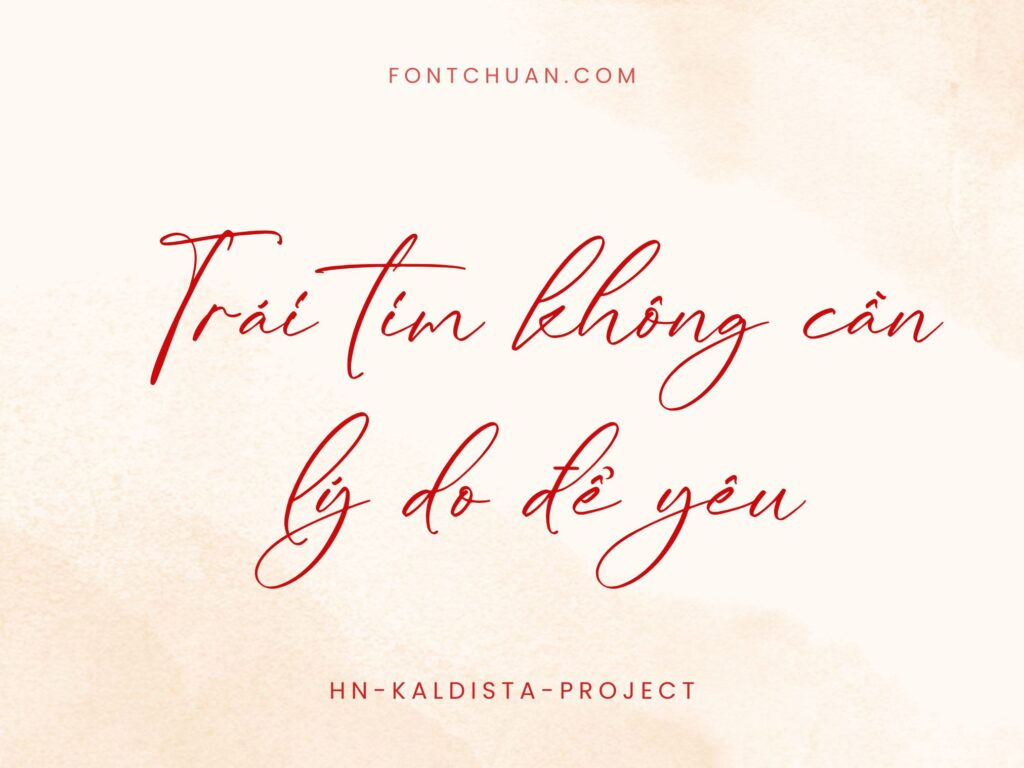
Font Kaldista Project Việt Hóa
Kaldista Project là một phông chữ chữ ký hiện đại, được thiết kế bởi **Glorytype Studio**. Phông chữ này mang phong cách viết tay tinh tế, phù hợp cho các dự án như logo, thương hiệu, thiết kế bao bì, thiệp mời và nhiều ứng dụng sáng tạo khác. Phiên bản HN Kaldista Project đã được Việt hóa bởi **Huy Nam**, hỗ trợ đầy đủ các ký tự tiếng Việt, giúp người dùng Việt Nam dễ dàng tích hợp vào các thiết kế địa phương. Việc Việt hóa này nhằm đáp ứng nhu cầu của cộng đồng thiết kế và giúp áp dụng vào các dự án thực tế.
Về đặc điểm thiết kế, Kaldista Project có các đường nét mềm mại và uyển chuyển, tạo cảm giác như chữ viết tay tự nhiên. Phông chữ này phù hợp cho các ứng dụng như thiệp mời, tiêu đề, bao bì sản phẩm và các dự án sáng tạo khác. Đồng thời, Kaldista Project cũng có thể được sử dụng như một Font chữ thiệp cưới, giúp các nhà thiết kế tạo ra những tấm thiệp cưới lãng mạn, tinh tế và sang trọng. Ngoài ra, Kaldista Project còn có thể được sử dụng như một Font chữ Giáng Sinh, lý tưởng để trang trí thiệp, poster hay banner mùa lễ hội, mang đến không khí ấm áp, vui tươi và sinh động cho các sản phẩm thiết kế.